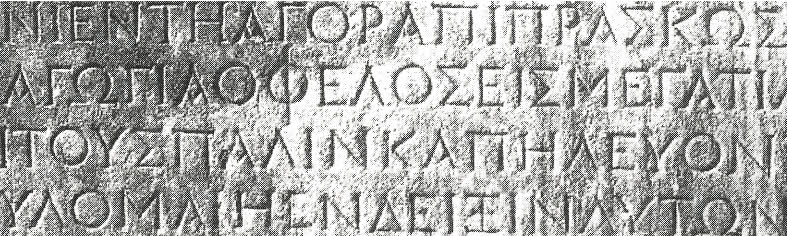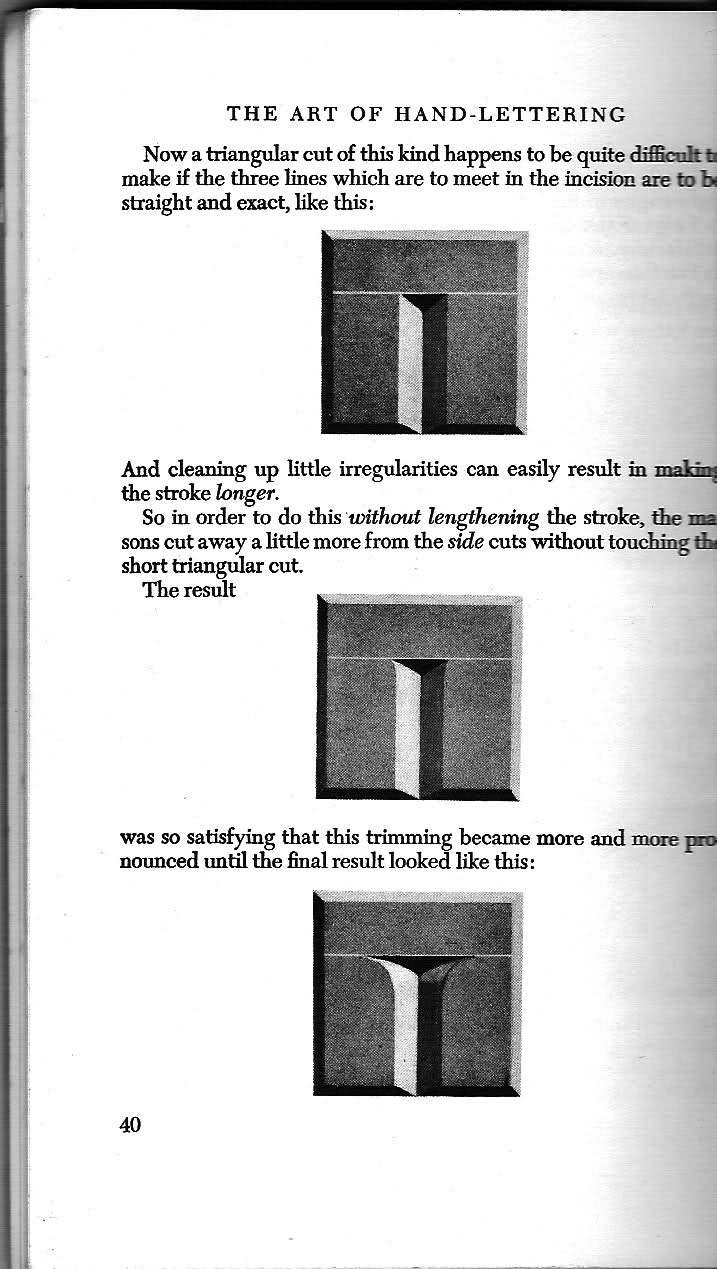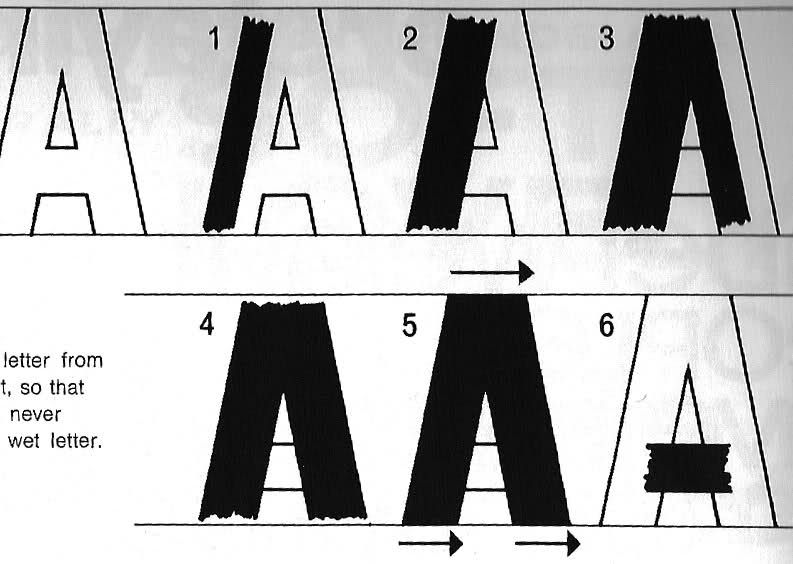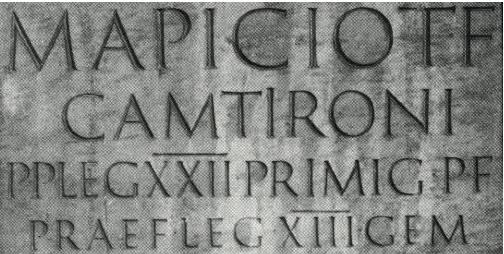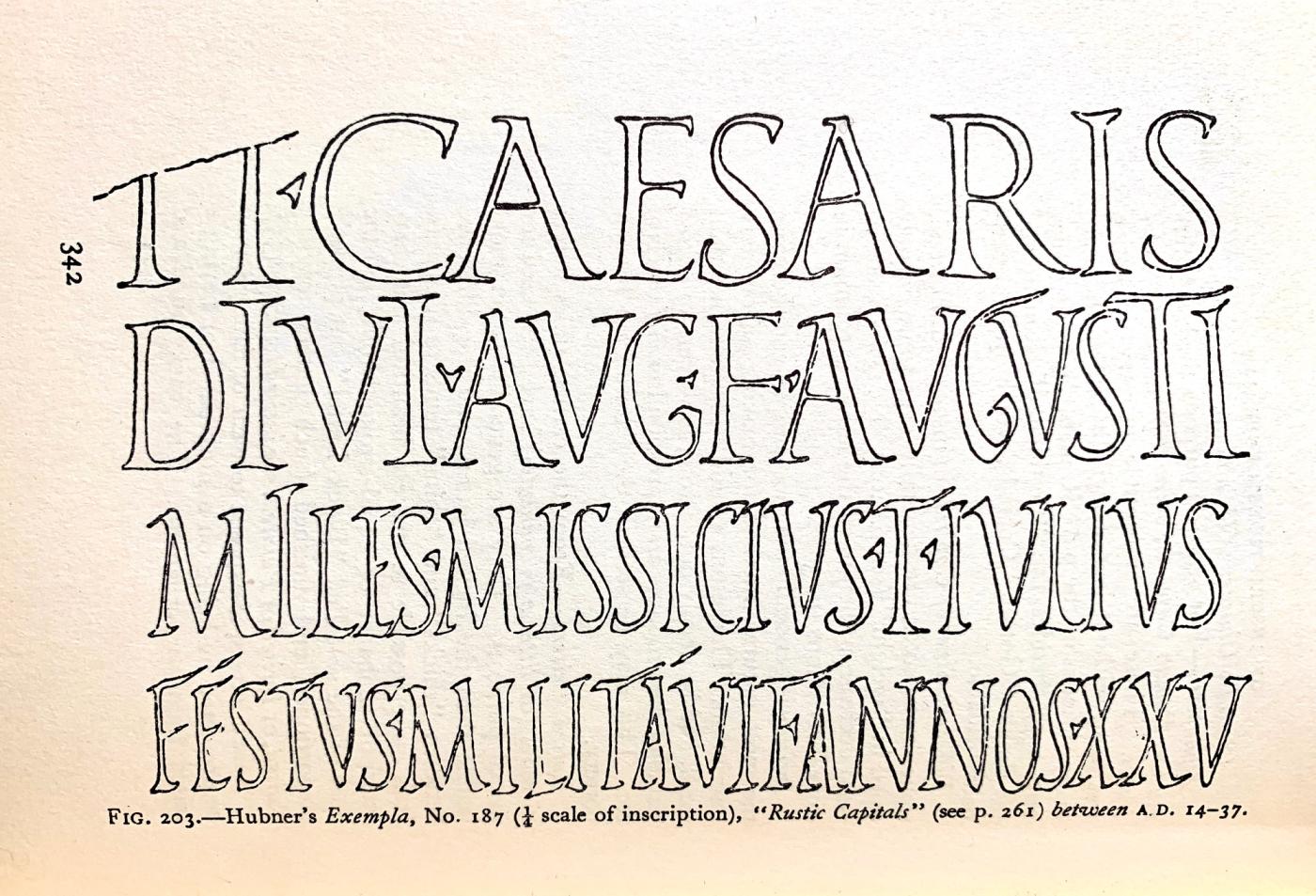
Schriftgeschichte: Wie enstanden die Serifen?
wie sind denn die Serifen entstanden?
Das ging ja wohl erst los, als die Römer ihre Capitalis Monumentalis in Stein meißelten; da sind ansatzweise Serifen zu entdecken. Mit "verbesserte Lesbarkeit" kann das ja damals noch nichts zu tun gehabt haben, da ja Text damals sowieso nicht in großen Mengen konsumiert wurde, sondern wenn dann laut vorgetragen wurde.
Oder bildeten sich die Serifen durch den Anstrich der mit der Rohrfeder niedergeschriebenen Capitalis?
Aha!? Aber zeitlich zu Verorten ist das ja dann auch Anfang/Mitte des ersten Jahrtausends, oder?
Wobei für mich keines der genannten Beispiele/Ursprünge wirklich "legitim" ist, denn damals waren die Serifen (oder das, woraus sie dann entstanden) ja nur eine (zwangsläufige) Begleiterscheinung des Schreibens, nicht bewusst verwendetes Gestaltungsmittel. (Oder?)
//edit: D'oh, hatte nur die deutsche wiki gelesen. Im Englischen findet sich:
Serifs are thought to have originated in the Roman alphabet with inscriptional lettering—words carved into stone in Roman antiquity. The explanation proposed by Father Edward Catich in his 1968 book The Origin of the Serif is now broadly but not universally accepted: the Roman letter outlines were first painted onto stone, and the stone carvers followed the brush marks which flared at stroke ends and corners, creating serifs.
Kommt vom Pinsel als Schreibwerkzeug …
Also ich habe gelernt, daß die Serifen vom Meißel als »Schreibwerkzeug« kommen. Wurde die römische Capitalis in Stein gehauen, wurde am Ende einer Linie ein Flachmeißel quer angesetzt und am Linienende eingeschlagen. Die herausplatzenden Füße ergaben das Urbild der Serife.
Schau dir mal die Original-Inschriften oder originalgetreu digitalisierte Schriften dieser Art an. Die Serifen sind in der Horizontalen in keiner Weise flach – die Flachmeißel-Theorie ist eine reine Kopfgeburt, die nichts mit der Realität gemein hat. Die Serifen zeigen viel mehr ganz klar die auslaufenden Abstriche der Pinsel-Vorzeichnungen. Ich meine mich zu erinnern, dass man in Pompeji sogar noch solche Vorzeichnungen finden konnte. Die Steinmetze haben die Form überhaupt nicht beeinflusst, sondern nur detailgenau ausgeformt, was der Schreiber vorher mit dem Pinsel vorgezeichnet hat.
Na, vielleicht gibt es ja hier einen Steinmetz, der das aufklären kann. Ich hab auch nur die Meißel-Theorie gehört, so hab ich es noch im Kopf: Die Serifen entstanden durch die schräge Meißelhaltung am Ende des Buchstaben. Dort musste man dann einen Abschluss finden für das "Tal", was entstanden ist. Und gerade heruntermeißeln geht ja nicht, also meißelt man einmal von links und einmal von rechts in die Mitte (schwer zu erklären). Da musste man meist ein wenig mehr Spielraum haben, als da war. Irgendwann fand man diese Mini-Serifen ästhetisch und vergrößerte sie. Voilà!
Wenn die Pinsel-Theorie also stimmt - von was ich nun ausgehe - dann gilt nun zu klären:
Wieso zeichneten die Vorzeichner ihre Buchstaben mit Serifen?
Ja, ist die Frage, womit die Jungs tatsächlich gemalt haben. Also ein Flachpinsel kann ja einen geraden Balken malen. Mit einem spitzen, runden Pinsel kann man eigentlich alles und auch sehr präzise malen. Aber ich denke, dass, wenn das untere Ende eines Buchstaben nicht ganz gerade geworden ist und man versucht es auszubessern, durchaus etwas Serifen-ähnliches herauskommen kann, vor allem mit dem flachen Pinsel.
Ich hab noch mal die Quelle mit dem Meißel eingefügt, allerdings ist dieser Mensch eher aus der Praxis, als aus der Theorie. Deshalb lege ich meine Hand nicht dafür ins Feuer. (Helm Wotkow, The Art of Hand Lettering)
Naja, zumindest die römische Schreibschrift scheint ja keine Serifen zu haben, außer diesen Slab-Serifen, die manchmal am Buchstabenstamm auftauchen.
Ja, ist die Frage, womit die Jungs tatsächlich gemalt haben. Also ein Flachpinsel kann ja einen geraden Balken malen.
Aber am Anfang und Ende entsteht dann kein ordentlicher Abschluss, deshalb muss man da den Pinsel einmal kurz horizontal aus dem Stamm rausziehen – der Symmetrie wegen natürlich nach beiden Seiten – voilà: die Serife ist da.
Ja, könnte man sich vorstellen. Heutzutage scheint man aber eher einen Querstrich zu bevorzugen, dann hat man auch einen geraden Abschluss. (Handlettering Today, Abraham Switkin)
Ich muss Alpha zustimmen -- wer schon mal Schrift in Stein gehauen hat weiß, wie brutal schwer es ist keine Serife zu machen. Ein bisschen Ecken ergeben sich fast zwangsläufig.
Das geht mir mit dem Pinsel oder der Feder nicht so, und schon gar nicht auf beiden Seiten. Das ist nämlich ordentlich schwer, Schriften wie die Kapitalis mit dem Pinsel zu schreiben, zeichnen geht schon eher.
Was jedoch auch sehr schwer ist, ist in Stein hauen ohne Vorzeichnung ...
Na, ich weiß es noch vom Kalligrafieunterricht mit der Feder: Das ist der Horror mit dem Ding Serifen hinzukriegen, vor allem auf der rechten Seite vom "T". Dabei muss man die Feder in unnatürlichem Winkel drehen. Was beim Malen mit dem Pinsel (wenn die Borsten nicht lang genug sind) entsteht, ist eine leichte Verdickung am Anfang und am Ende des Striches. Aber ob sich daraus Serifen entwickelt haben ... eine gewagte Theorie. Ich denke hier hilft einem nur das Experiment mit dem Meißel bzw. einem antiken Pinsel. Das mit den gemalten Serifenschriften als Argument ist auch nur schwach, da, wenn man, wie oben angedeutet, Serifen hauen will, wohl auch welche vormalt. Wie sah das eigentlich bei den Griechen aus, weiß das jemand? Hatten die schon Serifen an ihren Schriften/Inschriften?
Abb.: Emil Hübner: Exempla Scripturae Epigraphicae Latinae, Berolina 1885, No 187, Rustic Capitals.
Die Serifen zeigen viel mehr ganz klar die auslaufenden Abstriche der Pinsel-Vorzeichnungen. Ich meine mich zu erinnern, dass man in Pompeji sogar noch solche Vorzeichnungen finden konnte.
Ralf Herrmann zeigt solche Beispiele in seinem Artikel Warum die Serifen doch nichts mit dem Meißel zu tun haben. Findet sich hier auf Typografie.info :-)